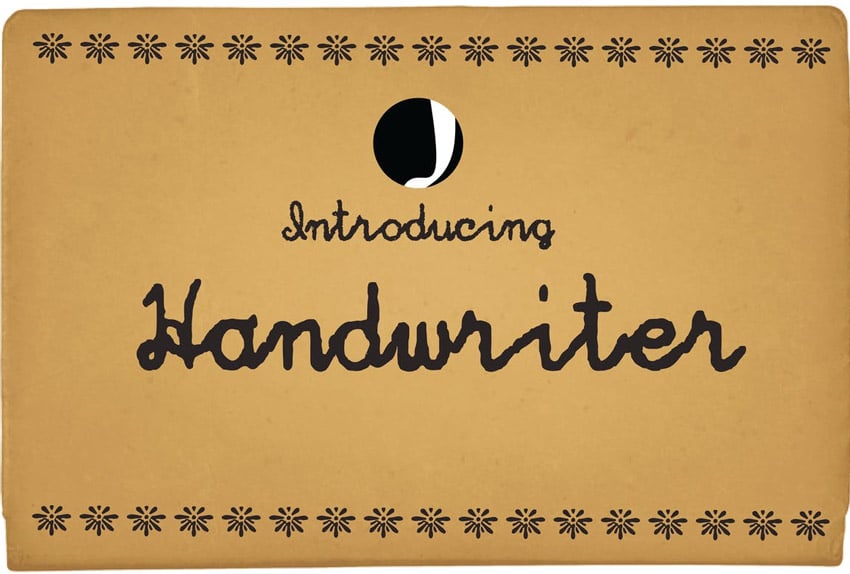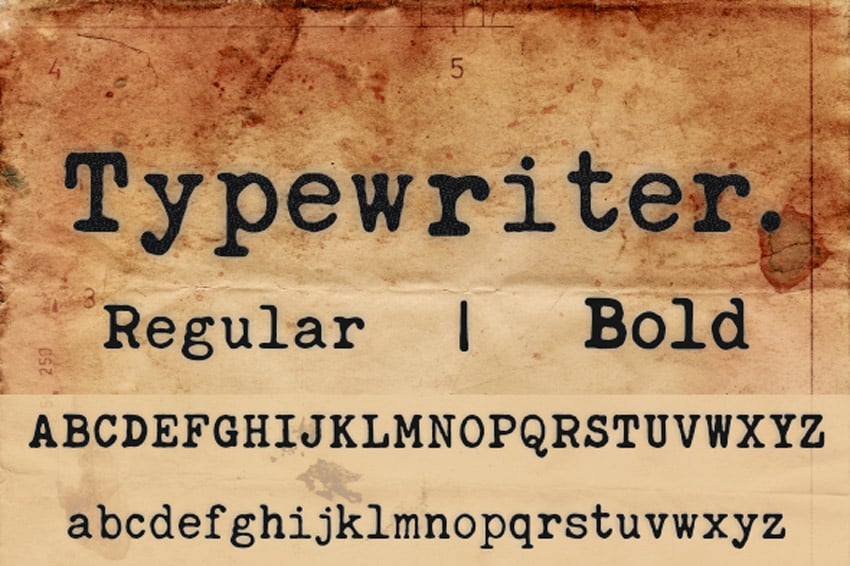
20+ Лучших Классических Машинописных Шрифтов в Стиле Старых (Винтажных) Печатных Машинок
Отдайте должное прошлому с красивой типографикой. Просмотрите этот выбор премиальных шрифтов в стиле пишущей машинки.
20+ Лучших Классических Машинописных Шрифтов
Помните пишущие машинки?
Печатание на пишущей машинке требовало определённого уровня усилий, которые многие молодые творческие работники никогда не увидят. И теперь вы можете выделить свои любимые винтажные стили с помощью высококачественных печатных шрифтов.
Сегодня мы представляем вам ещё одну отличную подборку ресурсов премиум-класса от Envato Market и Envato Elements с более чем 20 феноменальными шрифтами в стиле пишущих машинок, созданными в соответствии с классическими ретро печатными машинками. От гранжевых текстур до жирных шрифтов, эти стили исключительно универсальны.
Добавьте небольшую зернистость или ретро-текстуру к своим приглашениям, постерам и обложкам книг с помощью простого машинописного шрифта. Насладитесь этой коллекцией премиальных ресурсов, созданных нашим талантливым сообществом.
Шрифт Manson Font Family
Ищете современный машинописный шрифт? Тогда посмотрите на невероятное семейство шрифтов Manson. Обладая серией лёгких, обычных и смелых стилей, это семейство шрифтов хорошо разработано для получения чистого результата. Создайте выразительную кампанию, которая соответствует вашему бренду с семейством шрифтов Manson.
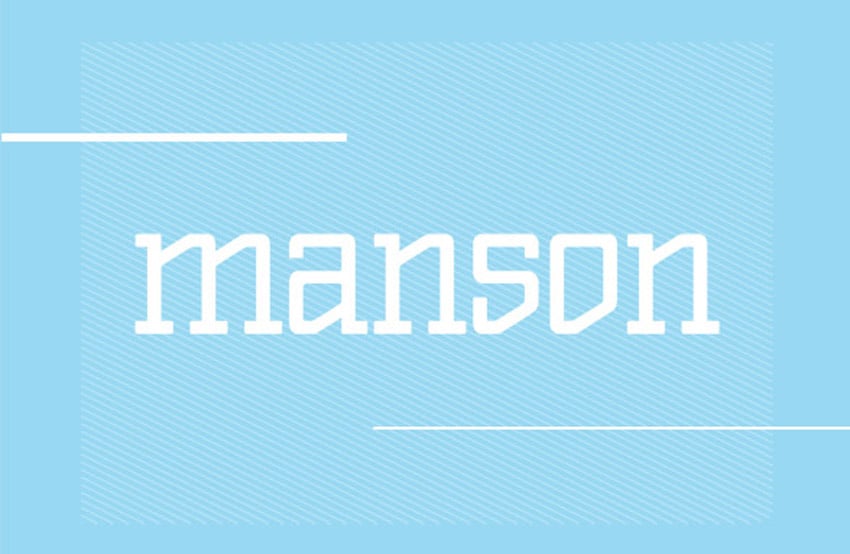
Шрифт Catalina Typewriter
Создайте дизайн заголовков и абзацев с помощью этого машинописного шрифта Catalina. Этот шрифт имеет классический внешний вид в стиле пишущей машинки с крутым, нарисованным вручную росчерком. Исследуйте шесть удивительных стилей шрифтов, которые соответствуют вашим потребностям. Выберите из светлого, обычного и жирного стилей.
Шрифт Enigma Typewriter Sans
Напишите сообщения в стиле загадки. Машинописный шрифт Enigma поможет вам воссоздать эффект старых документов и писем с винтажной точностью. Вдохновлённый стилем немецкой машинки, шрифт Enigma полон характера и очарования. Проверьте его на канцелярских принадлежностях и постерах.
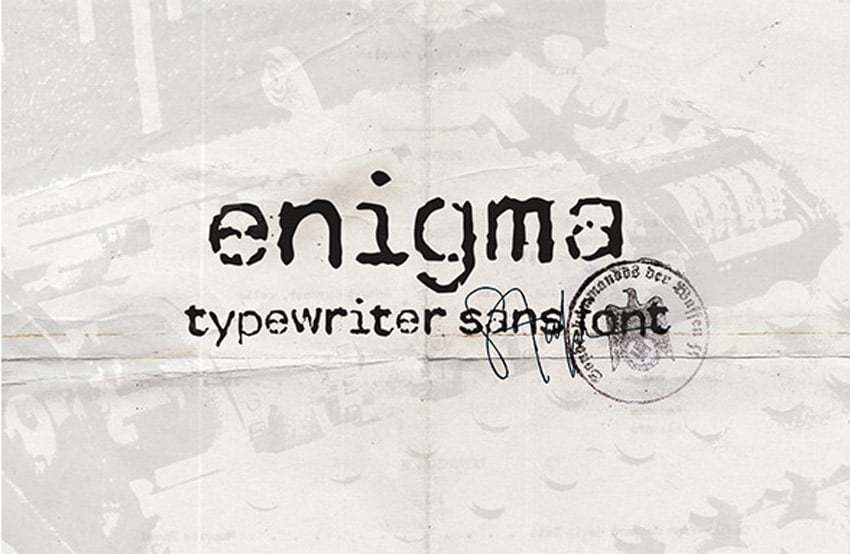
Шрифт Not My Type Typewriter
Вот ещё один отличный машинописный шрифт, который можно добавить в свою коллекцию! Этот шрифт, содержащий фактический текст, написанный на старинной пишущей машинке Oliver, использует три варианта для каждой буквы. Вы также можете включить дополнительные контекстные альтернативы, чтобы буквы менялись по мере ввода.
Шрифт Postmark Typewriter
Оставьте свой след в мире с этим винтажным шрифтом. Машинописный шрифт Postmark изготовлен вручную и хорошо продуман. Благодаря шрифту с современной текстурой, этот эпический шрифт включает как обычные, так и эскизные стили. Добавьте его к своим ретро постерам сегодня!
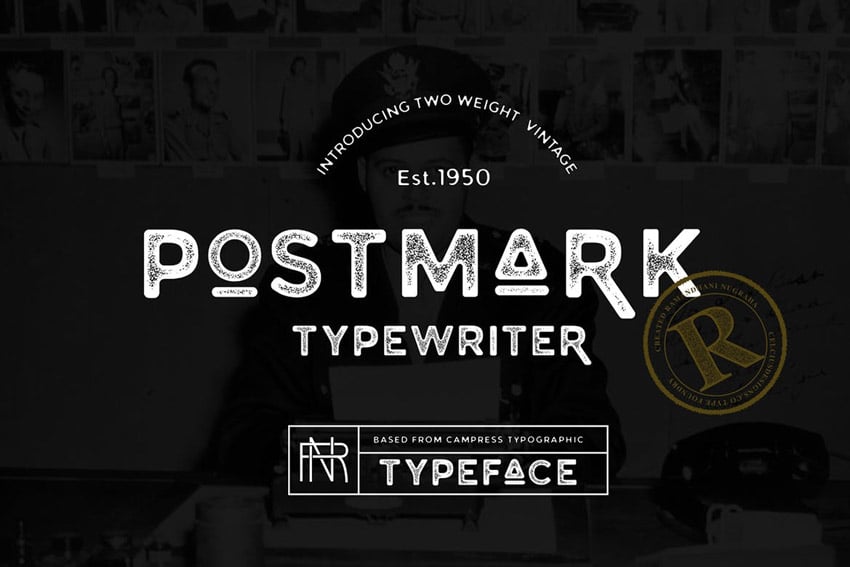
Шрифт Classica — Hatched Typewriter
Вдохновлённый стилем известной пишущей машинкой, этот шрифт выглядит как настоящий. Шрифт Classica сочетает в себе традиционные печатные буквы с уникальным штрихованным эффектом для придания большего колорита. С лёгкостью загрузите файлы TrueType или OpenType, чтобы начать использовать этот шрифт. Отлично подходит для любого любителя винтажа!
Шрифт Windflower
Украсьте текст своей машинки красивыми цветами! В наборе шрифтов Windflower имеется полное семейство шрифтов, чтобы перенести вашу работу на новый уровень. Насладитесь прекрасной смесью деликатных деталей и жирных заглавных букв. Идеально подходит для скрапбукинга, постеров или любого домашнего проекта.
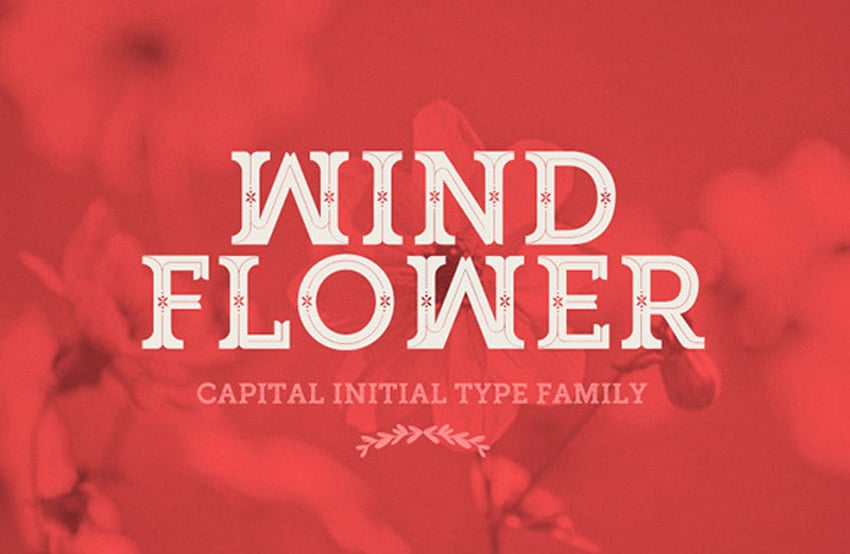
Шрифт Newstyle Typeface
Передайте в эфир самые последние заголовки и истории с этим исключительным шрифтом Newstyle. Современный вид традиционного шрифта пишущей машинки, этот шрифт чистый и эффективный. Воспользуйтесь уникальным стилем, чтобы ваш бренд выделялся. В эту загрузку включены несколько стилей шрифтов и простое руководство пользователя для получения дополнительной информации.
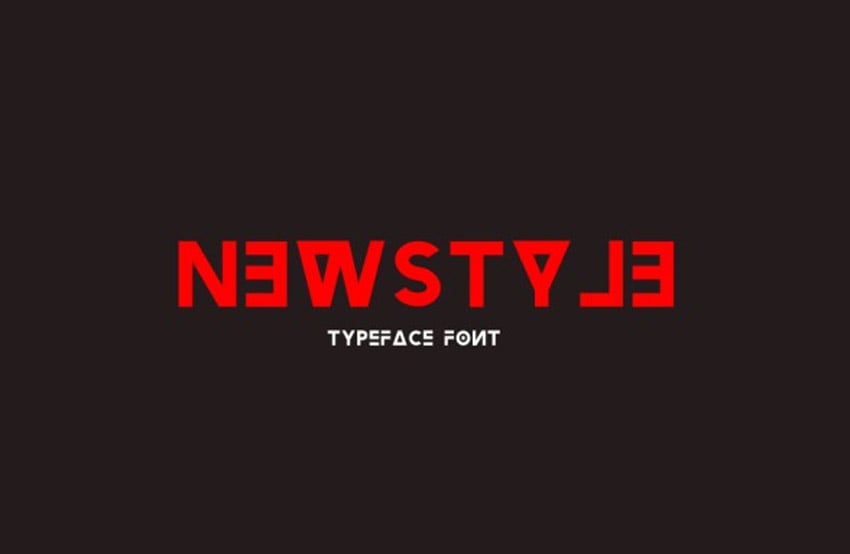
Шрифт Detective — Typewriter
Раскройте свои скрытые увлечения с помощью машинописного шрифта Detective. Классический механический шрифт с аутентичным стилем пишущей машинки, этот шрифт лёгкий и простой. Просто вставьте его в ваш следующий проект для создания реалистичного машинописного текста. Или используйте его для деловой переписки в качестве персонального штриха!
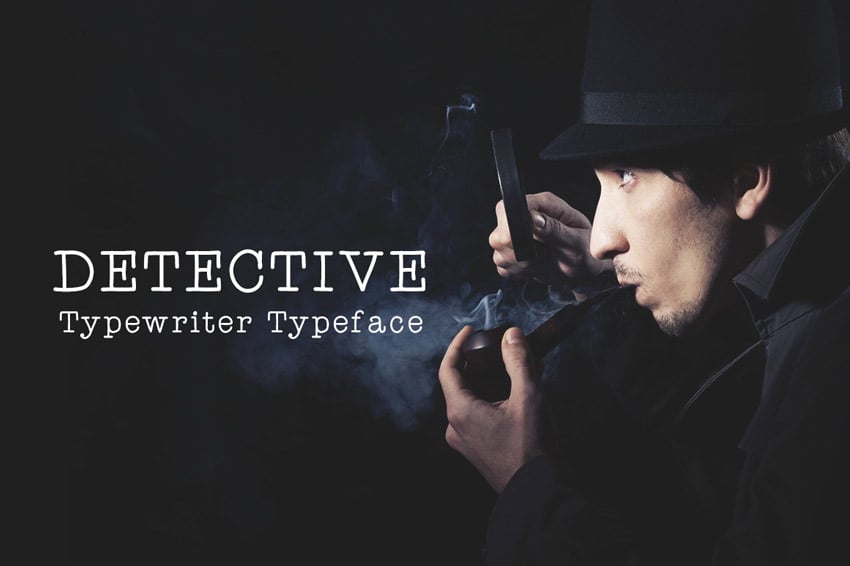
Шрифт Abegnale Classic
Классические печатные шрифты, такие как шрифт Abegnale, очень важны для дизайнеров. Придавая вам подлинное ощущение высокой печати, этот шрифт превращает любую старую открытку в реалистичный, выветренный вид. Соедините его с другими винтажными шрифтами для большего количества вариаций.
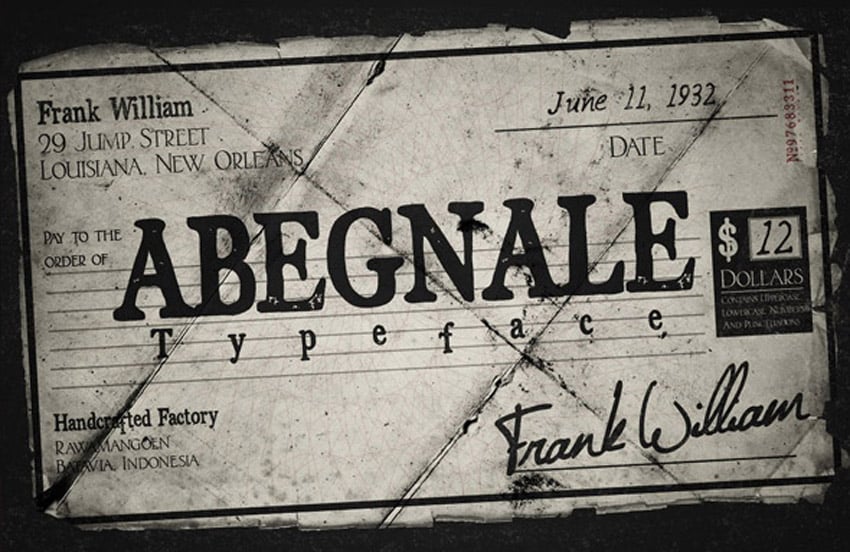
Шрифт Old Typewriter
Персонализируйте свои сообщения с помощью старых машинописных шрифтов. Получите доступ к файлам EPS и TTF с помощью этой простой загрузки. Этот стилизованный ретро-шрифт содержит полный набор букв, цифр и знаков препинания в одном пакете шрифтов. Попробуйте применить его на приглашениях и многом другом!